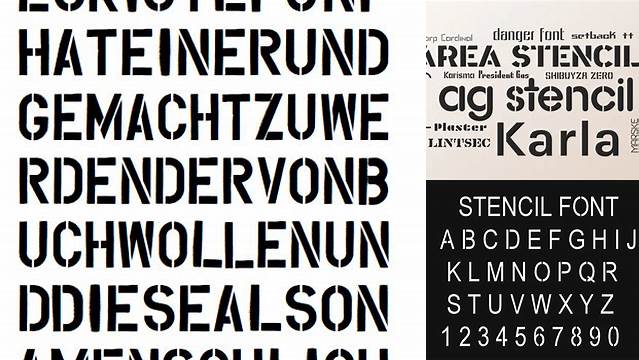
Font Cutting Terbaik: Panduan Memilih Untuk Hasil Sempurna
Memilih Font Terbaik untuk Cutting: Panduan Lengkap
Memilih font untuk cutting yang tepat adalah langkah krusial dalam berbagai proyek, mulai dari pembuatan stiker, dekorasi, hingga signage. Jenis font yang Anda pilih akan sangat memengaruhi hasil akhir, baik dari segi estetika maupun kemudahan proses cutting. Dalam panduan lengkap ini, kita akan membahas berbagai aspek penting dalam memilih font untuk cutting, termasuk jenis-jenis font yang paling cocok, faktor-faktor yang perlu dipertimbangkan, serta tips dan trik untuk mendapatkan hasil terbaik.
Mengapa Pemilihan Font Penting dalam Proses Cutting?
Pemilihan font untuk cutting bukanlah sekadar memilih huruf yang terlihat bagus. Ada beberapa alasan mengapa hal ini sangat penting:
- Kemudahan Cutting: Beberapa font memiliki desain yang rumit dengan detail-detail kecil yang sulit dipotong dengan mesin cutting. Font dengan garis yang terlalu tipis atau sudut yang terlalu tajam dapat menyebabkan hasil potongan yang tidak rapi atau bahkan merusak material.
- Keterbacaan: Font yang dipilih harus tetap mudah dibaca setelah dipotong dan ditempelkan. Font dengan desain yang terlalu rumit atau terlalu dekoratif mungkin terlihat menarik di layar, tetapi sulit dibaca dalam bentuk fisik.
- Estetika: Font yang tepat akan meningkatkan tampilan keseluruhan proyek Anda. Font harus sesuai dengan gaya dan tema proyek, serta menyampaikan pesan yang ingin Anda sampaikan.
- Efisiensi Waktu dan Biaya: Memilih font yang mudah dipotong akan menghemat waktu dan biaya produksi. Anda tidak perlu menghabiskan waktu untuk memperbaiki hasil potongan yang buruk atau mengganti material yang rusak.
Jenis-Jenis Font yang Cocok untuk Cutting
Ada berbagai jenis font untuk cutting yang tersedia, masing-masing dengan karakteristik dan keunggulan tersendiri. Berikut adalah beberapa jenis font yang paling populer dan cocok untuk proyek cutting:
- Sans-Serif: Font sans-serif adalah pilihan yang sangat baik untuk cutting karena desainnya yang sederhana dan bersih. Font ini tidak memiliki serif (garis kecil di ujung huruf), sehingga lebih mudah dipotong dan dibaca. Contoh font sans-serif yang populer adalah Arial, Helvetica, dan Futura. Font-font ini sangat ideal untuk proyek-proyek modern dan minimalis.
- Serif: Font serif memiliki serif di ujung huruf, yang dapat memberikan tampilan yang lebih tradisional dan elegan. Meskipun demikian, beberapa font serif mungkin sulit dipotong karena detail-detail kecilnya. Jika Anda ingin menggunakan font serif, pilihlah font dengan desain yang sederhana dan garis yang cukup tebal. Contoh font serif yang cocok untuk cutting adalah Times New Roman (dengan modifikasi ketebalan) dan Georgia.
- Script: Font script meniru tulisan tangan, yang dapat memberikan tampilan yang unik dan personal. Namun, font script seringkali memiliki desain yang rumit dengan banyak lekukan dan garis tipis, sehingga sulit dipotong. Jika Anda ingin menggunakan font script, pilihlah font dengan desain yang sederhana dan garis yang jelas. Hindari font script dengan terlalu banyak ornamen atau detail yang rumit. Contoh font script yang cocok untuk cutting adalah Brush Script dan Lucida Calligraphy (dengan penyesuaian).
- Display: Font display adalah font yang dirancang untuk menarik perhatian, seringkali digunakan untuk judul atau headline. Font ini memiliki berbagai macam gaya dan desain, mulai dari yang klasik hingga yang modern. Namun, beberapa font display mungkin sulit dipotong karena desainnya yang rumit. Jika Anda ingin menggunakan font display, pilihlah font dengan desain yang sederhana dan garis yang jelas. Perhatikan juga keterbacaan font setelah dipotong. Contoh font display yang cocok untuk cutting (dengan seleksi yang cermat) adalah Impact dan Bebas Neue.
- Stencil: Font stencil dirancang khusus untuk cutting, dengan desain yang memiliki celah atau bagian yang terputus. Celah ini memungkinkan bagian dalam huruf tetap terhubung dengan bagian luar, sehingga hasil potongan tidak terlepas. Font stencil sangat cocok untuk proyek-proyek yang membutuhkan daya tahan dan kekuatan, seperti signage atau dekorasi outdoor. Contoh font stencil yang populer adalah Stencil dan Army.
Faktor-Faktor yang Perlu Dipertimbangkan dalam Memilih Font untuk Cutting
Selain jenis font, ada beberapa faktor lain yang perlu Anda pertimbangkan dalam memilih font untuk cutting:
- Ketebalan Garis: Font dengan garis yang terlalu tipis mungkin sulit dipotong dan mudah patah. Pilihlah font dengan garis yang cukup tebal agar hasil potongan lebih kuat dan tahan lama. Ketebalan garis juga memengaruhi keterbacaan font setelah dipotong. Pastikan garis tidak terlalu tipis sehingga huruf tetap jelas dan mudah dibaca.
- Jarak Antar Huruf (Kerning): Jarak antar huruf yang terlalu rapat atau terlalu lebar dapat membuat font sulit dibaca. Pastikan jarak antar huruf seimbang dan proporsional. Beberapa software desain memungkinkan Anda untuk menyesuaikan kerning secara manual. Perhatikan juga bagaimana kerning akan memengaruhi proses cutting. Jarak yang terlalu rapat dapat menyebabkan bagian-bagian huruf saling menempel, sementara jarak yang terlalu lebar dapat membuat hasil potongan terlihat tidak menyatu.
Kesimpulan Akhir
Dalam memilih font untuk cutting, penting untuk mempertimbangkan berbagai faktor agar hasil akhir sesuai harapan. Mulai dari jenis font, ketebalan garis, hingga kemampuan mesin cutting, semuanya berperan dalam menentukan kualitas potongan. Guys, jangan terburu-buru dalam memilih font; luangkan waktu untuk bereksperimen dan menguji berbagai opsi. Ingatlah bahwa font yang mudah dibaca dan dipotong akan membuat proyek Anda terlihat profesional dan menarik. Dengan panduan ini, diharapkan Anda dapat membuat keputusan yang tepat dan menghasilkan karya cutting yang memukau. Selamat berkreasi!